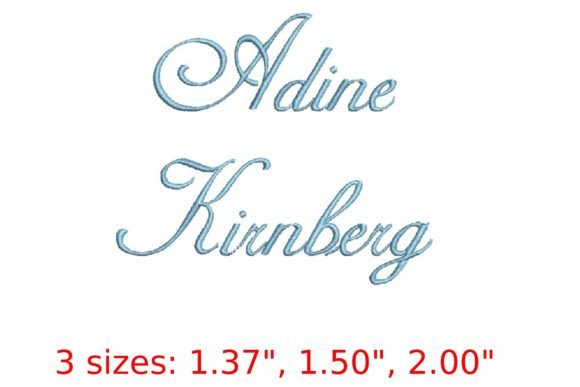
Adine Kirnberg Embroidery Font
Trouver les bons éléments de conception peut être un défi, mais Adine Kirnberg Embroidery Font propose une collection exceptionnelle qui rehausse instantanément votre travail.